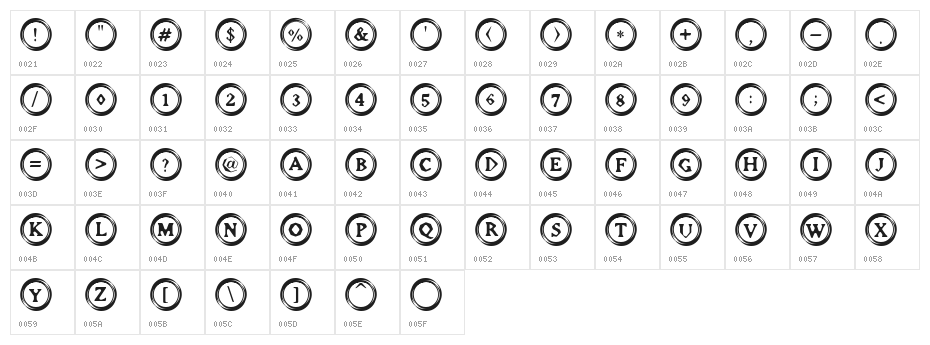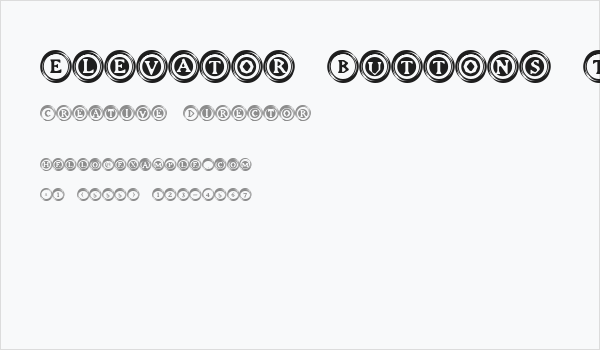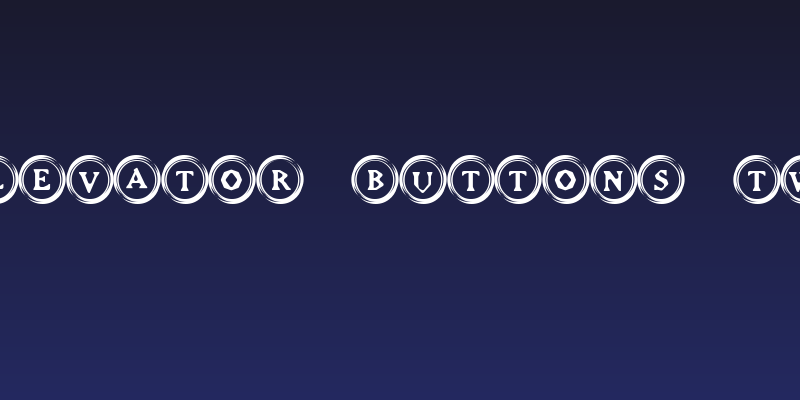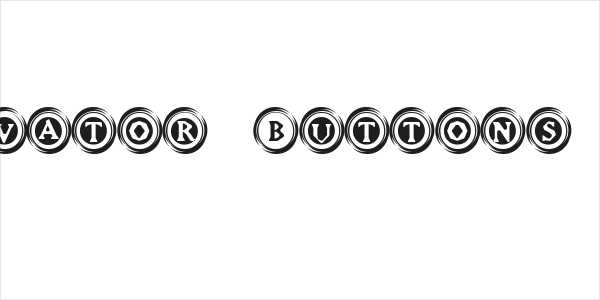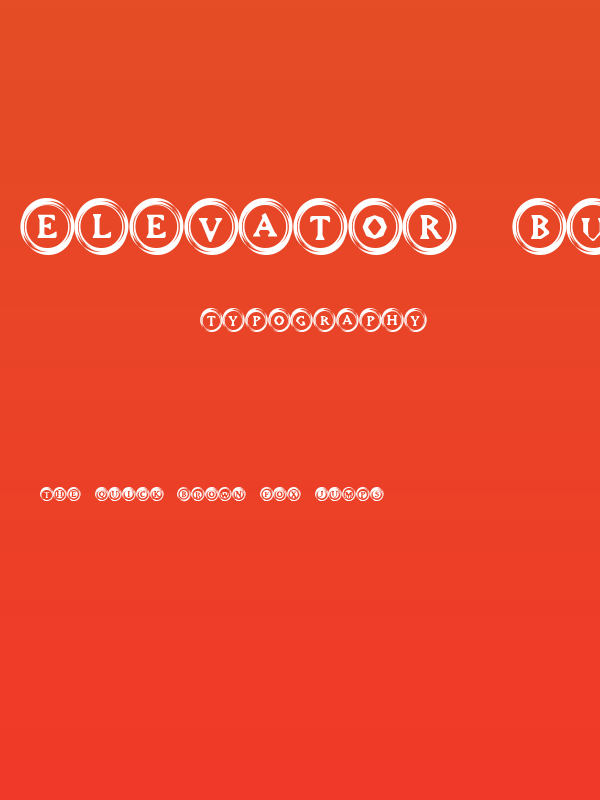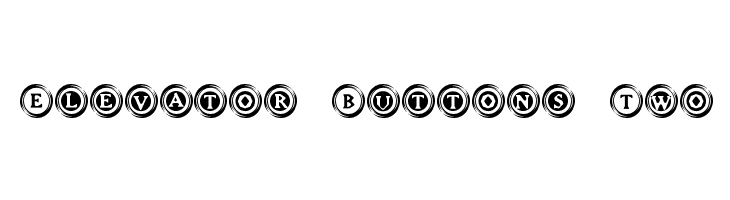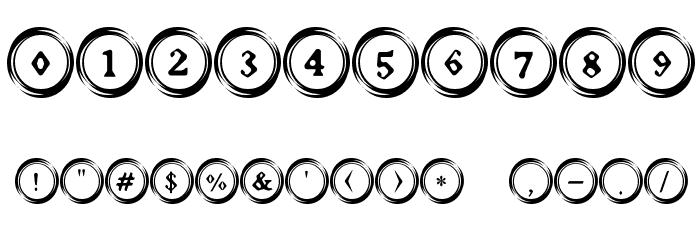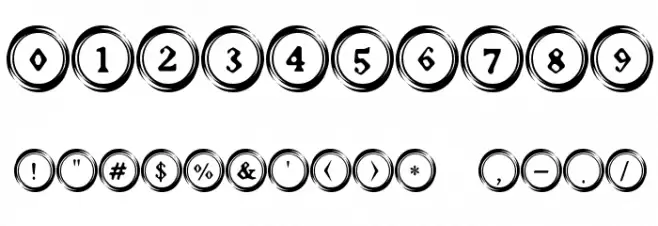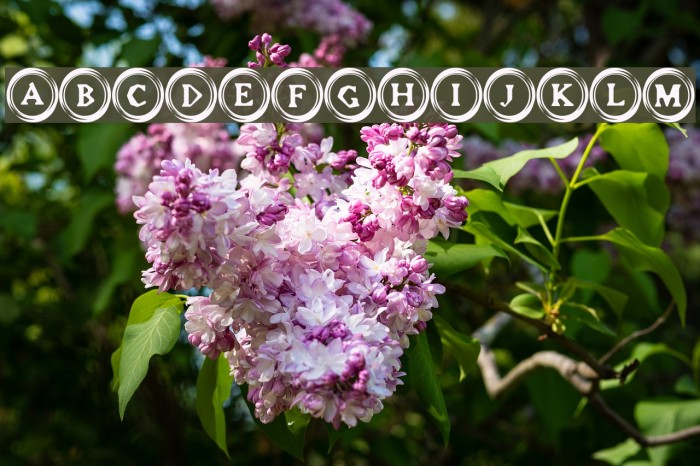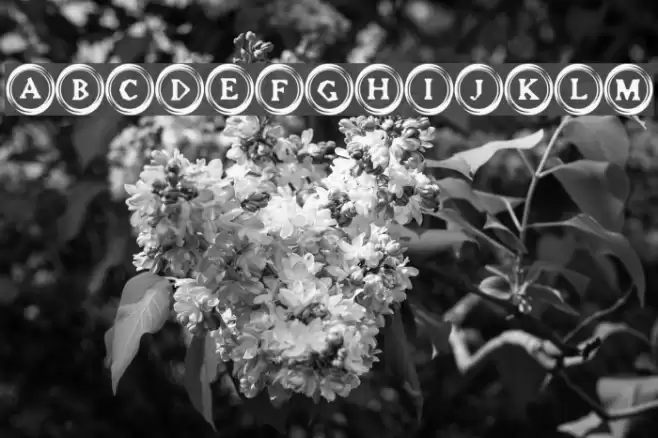
Elevator Buttons Two Font
| النمط العام | Vintage |
| حالة الاستخدام | Headlines, Logos, Signage |
| مشاريع مقترحة | Ideal for vintage-themed designs, signage, posters, and branding that require a distinctive and elegant appearance. |